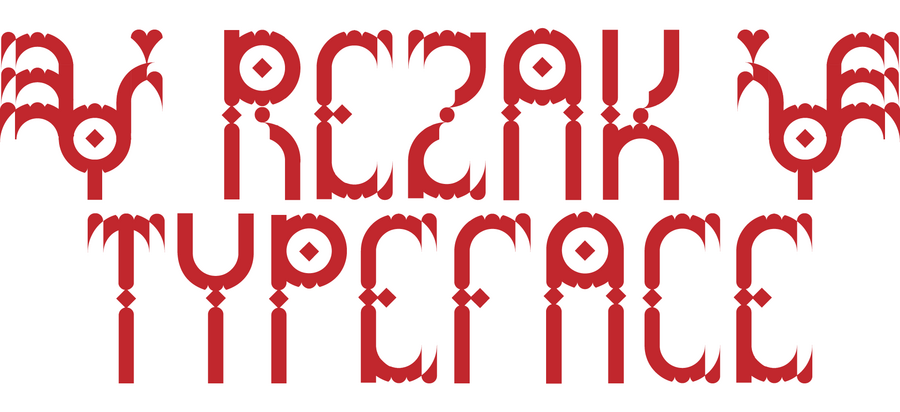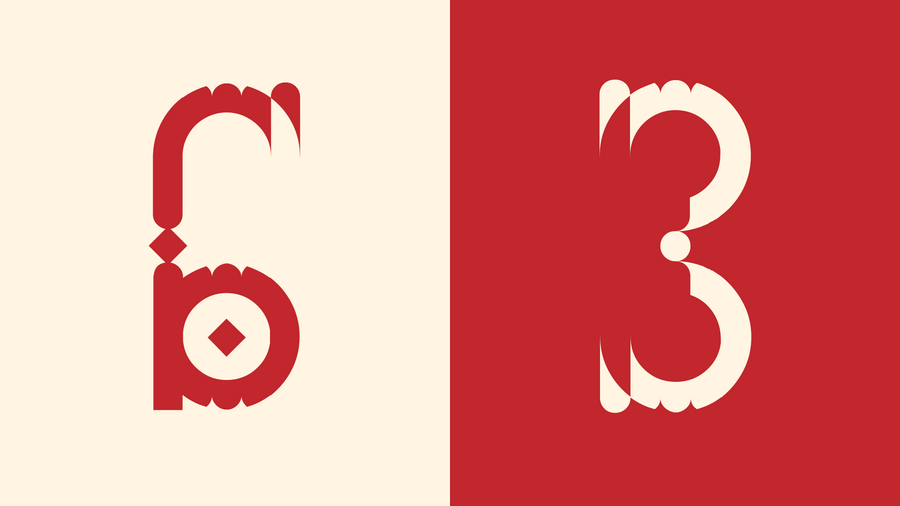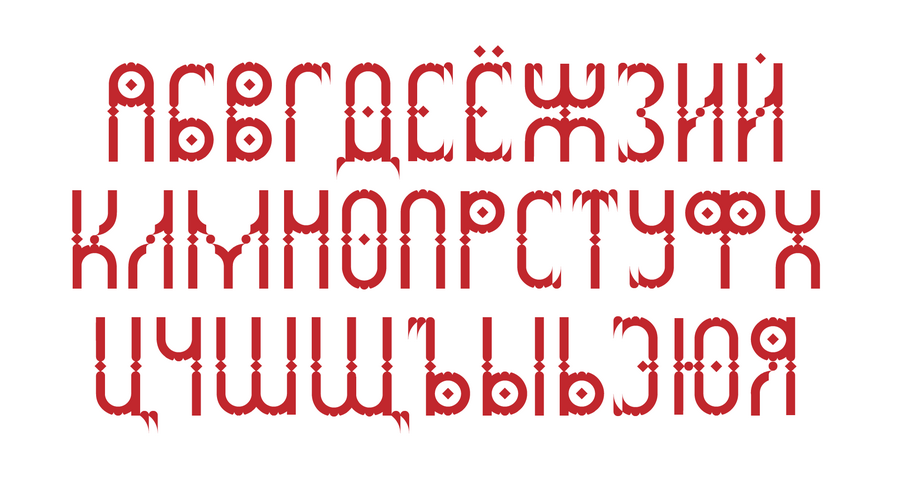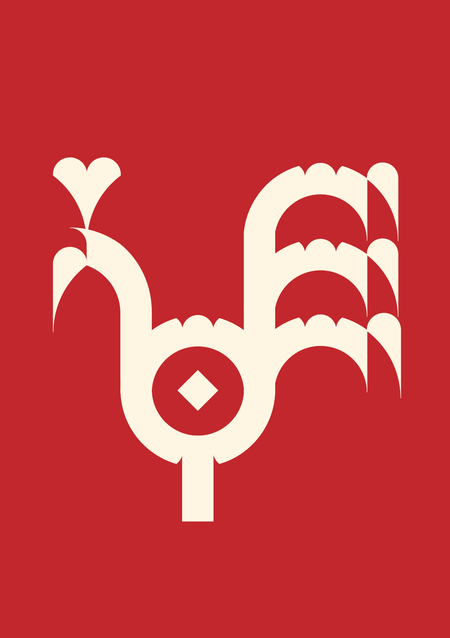
REZAK TYPEFACE — модульный шрифт, вдохновлённый резьбой по дереву и народными промыслами. В нём сочетаются округлые и прямые формы, острые углы и плавные переходы, а сами элементы выглядят так, словно высечены руками ремесленника